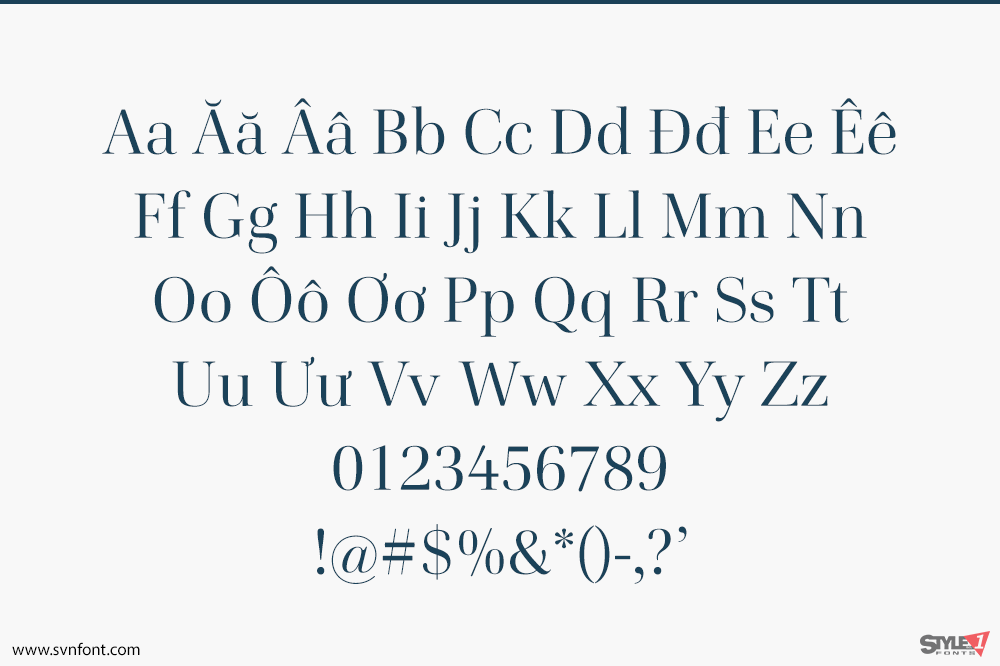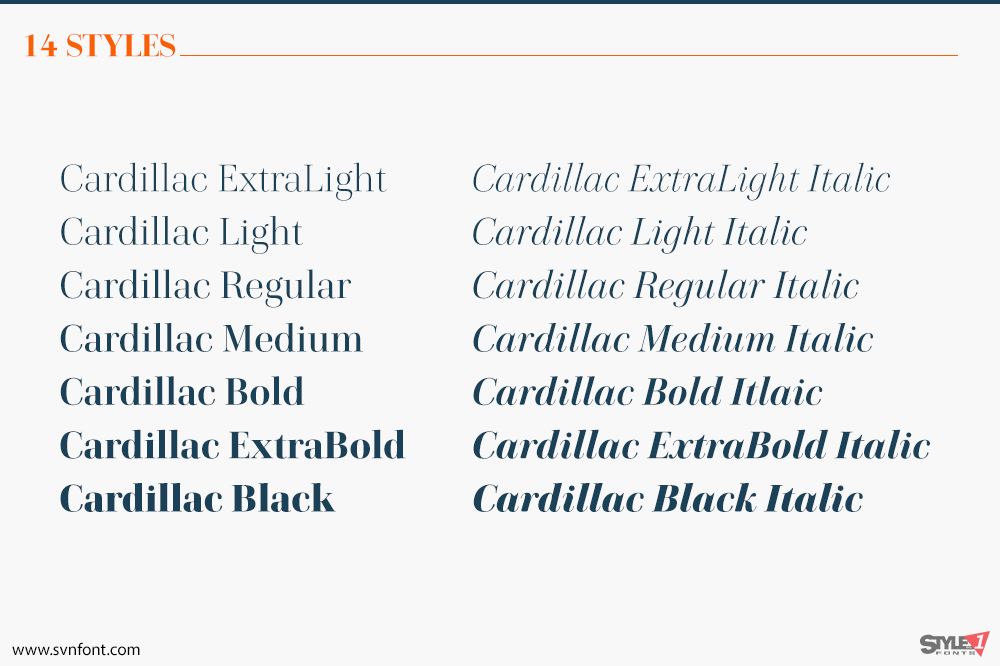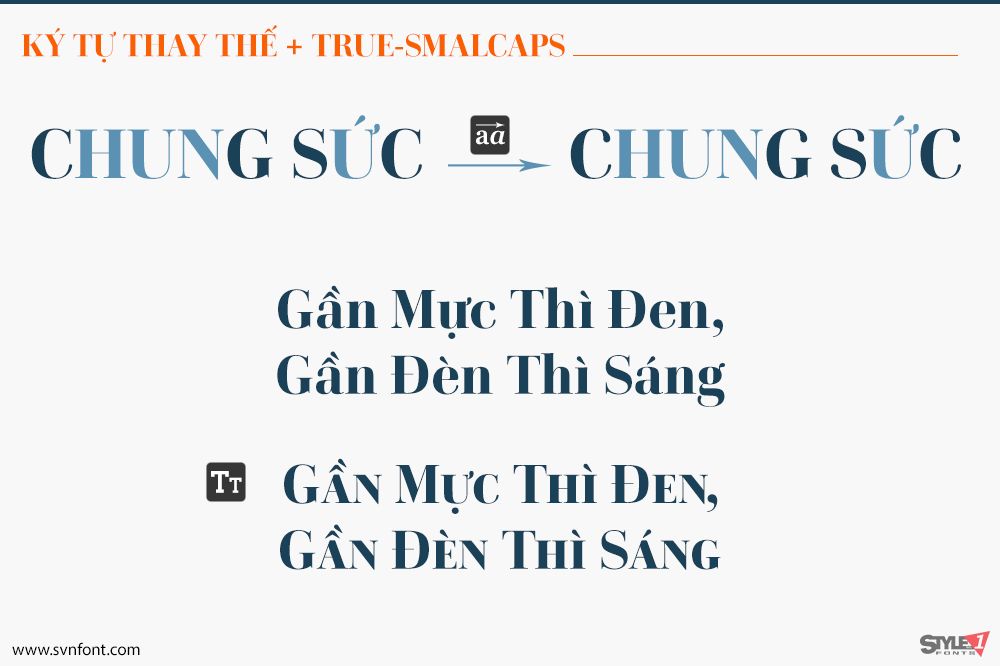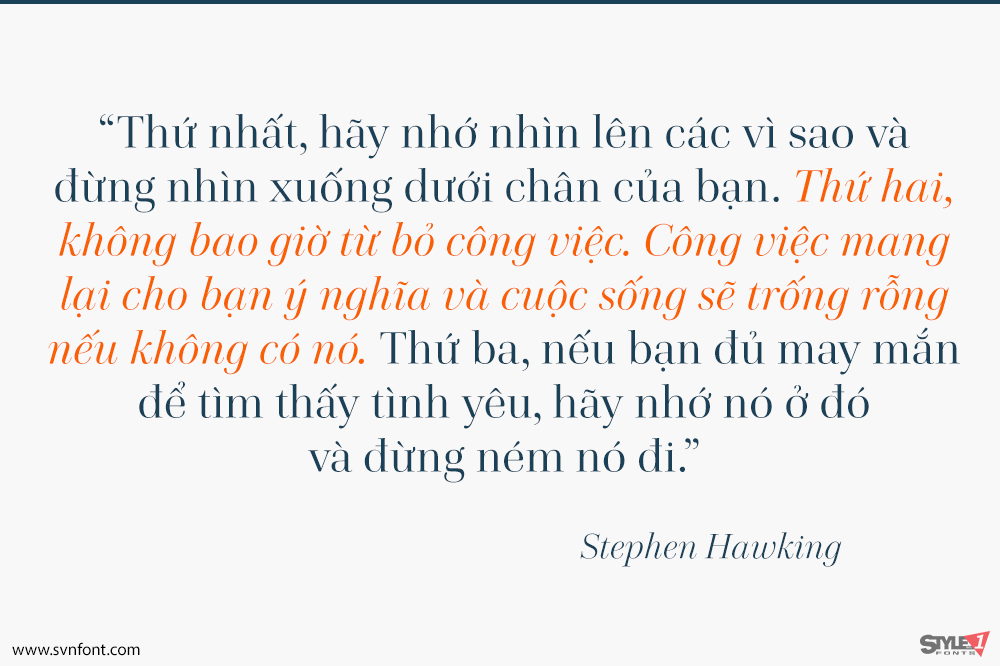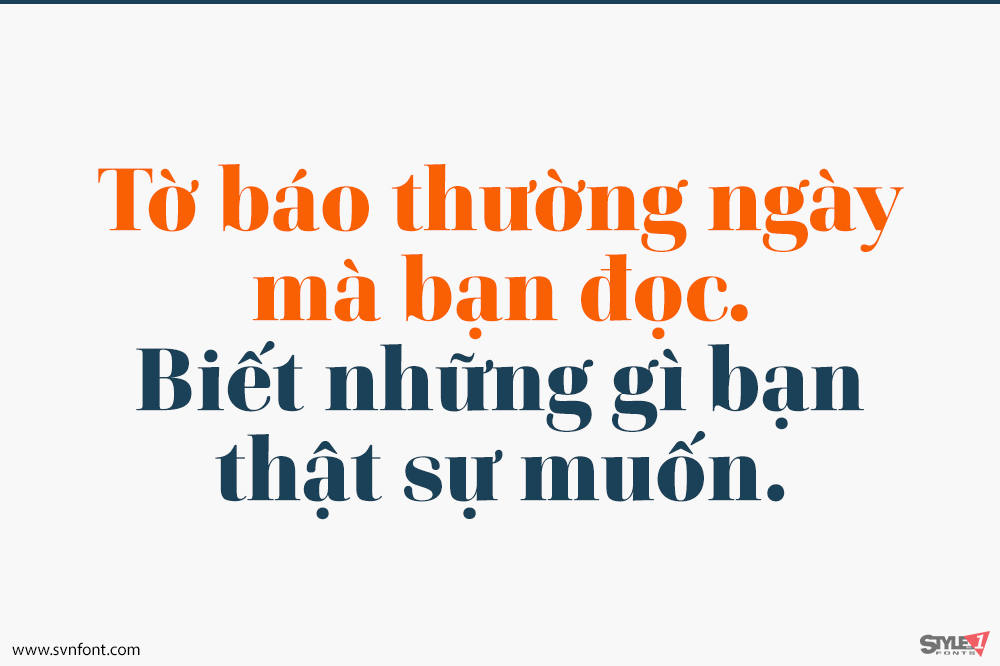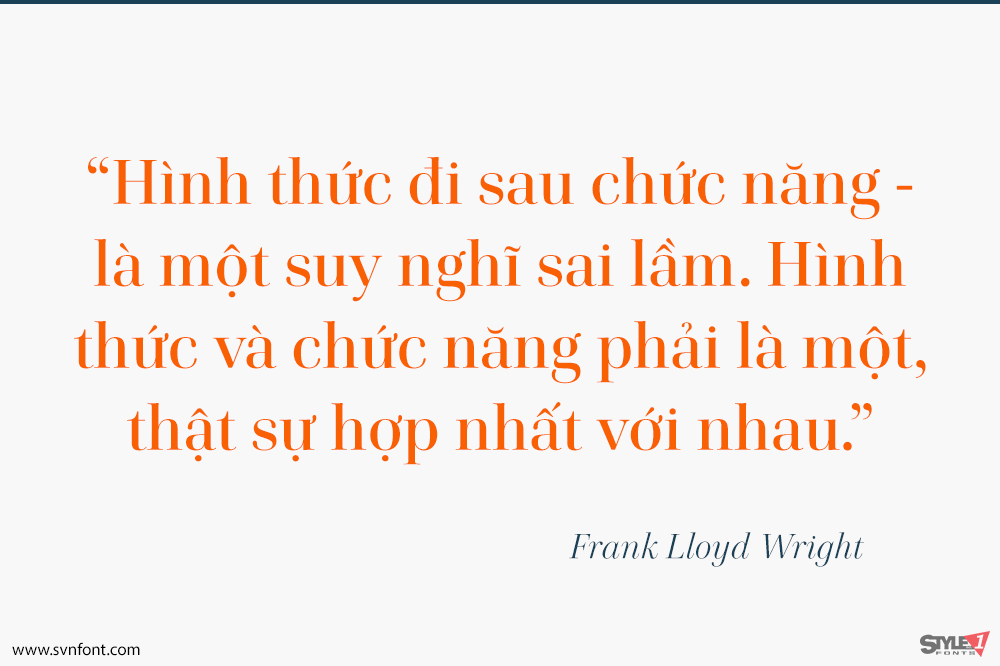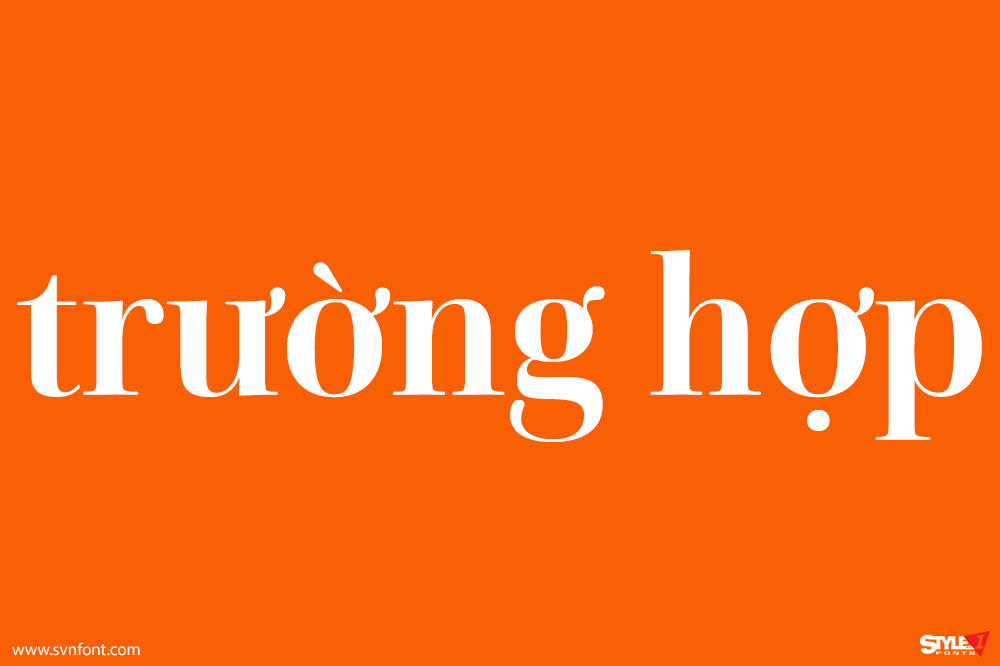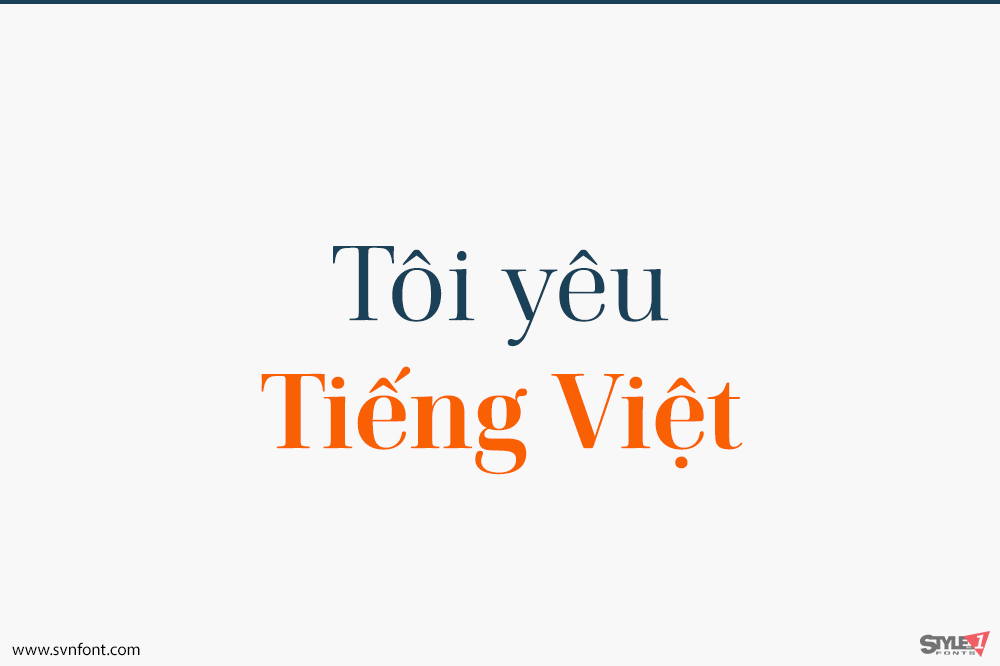
Cardillac, được đặt tên theo nhân vật văn học của E.T.A. Hoffmann, gợi nhớ đến phong cách Didone cổ điển nhưng lại có những chi tiết độc đáo tạo nên một hương vị mới, khác biệt so với các mẫu lịch sử. Sự rõ ràng, vẻ ngoài cao quý và sự thanh lịch lạnh lùng khiến nó rất phù hợp cho các tạp chí và báo. Bộ phông chữ Cardillac bao gồm 14 kiểu và cung cấp nhiều tính năng, cho phép ứng dụng vào các tác phẩm in ấn phức tạp. Nó có định dạng OpenType với hỗ trợ ngôn ngữ mở rộng.
Tất cả các độ đậm đều chứa các tính năng như chữ viết hoa nhỏ (small caps), chữ ghép (ligatures), ký tự trên dòng (superior characters), số thẳng hàng tỷ lệ (proportional lining figures), số thẳng hàng dạng bảng (tabular lining figures), số kiểu cổ tỷ lệ (proportional old style figures), số kiểu cổ thẳng hàng (lining old style figures), các ký hiệu tiền tệ tương ứng, phân số và chữ số khoa học, mũi tên phù hợp và các ký tự thay thế.
Nhà thiết kế: Dieter Hofrichter
Nhà phát hành: Hoftype